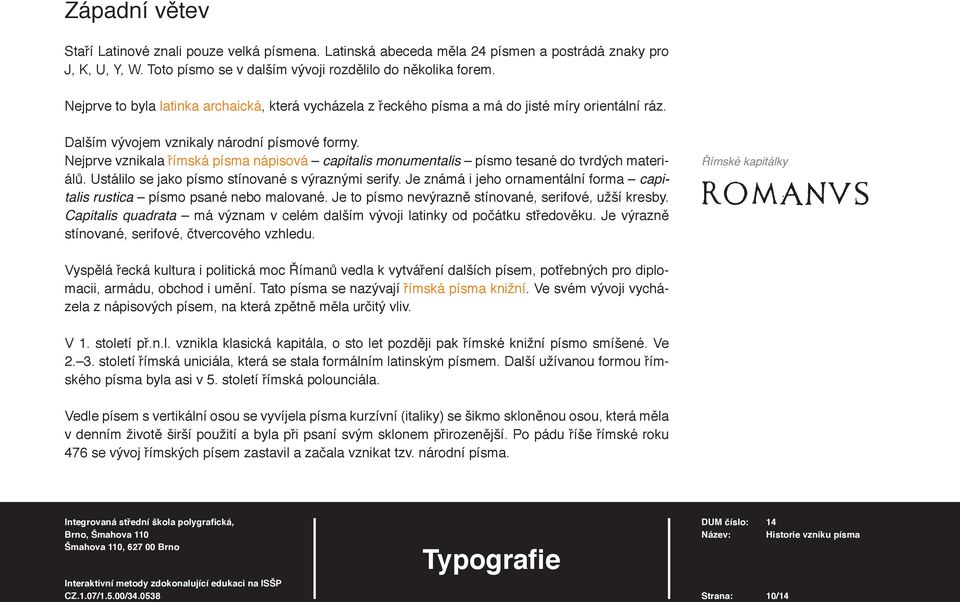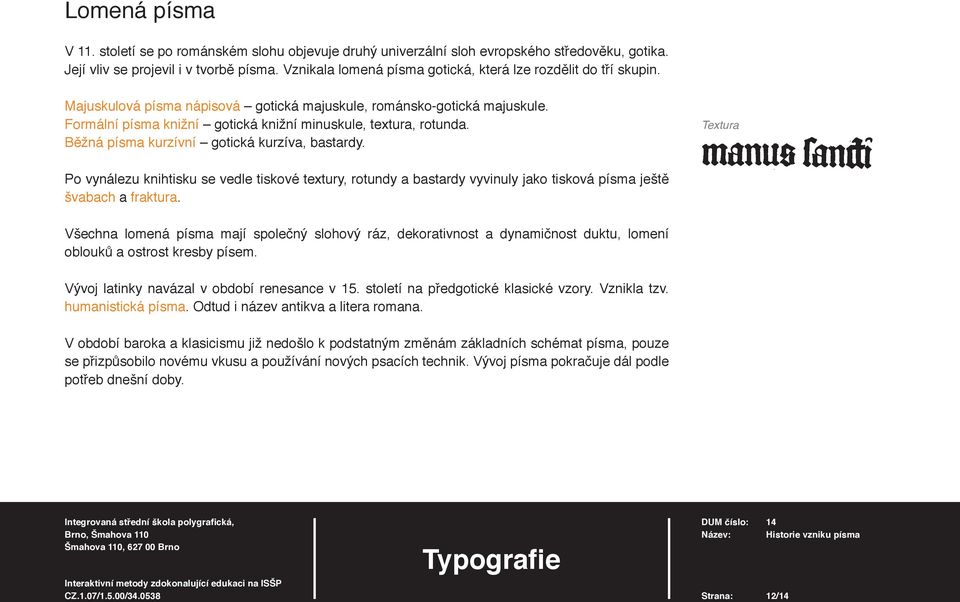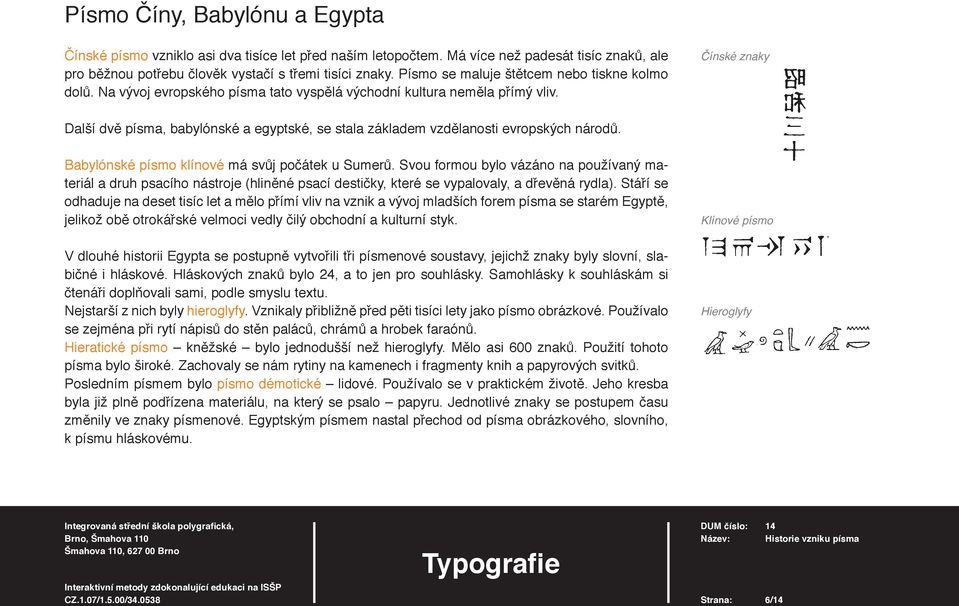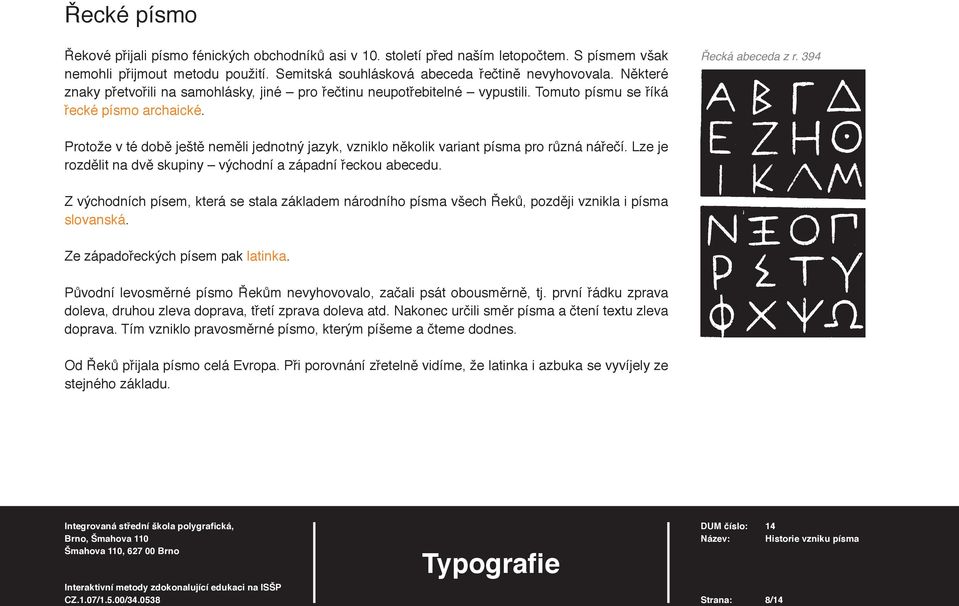
14. Historie vzniku písma. Typografie
1 14. Historie vzniku písma Vytvořila: Ivana Michálková Vytvořeno dne: Strana: 1/14
3 Řeč a písmo Podmínkou vzniku řeči a později písma byla praktická činnost lidí a společenský charakter práce, který vyžadoval vyjadřování a zaznamenávání myšlenek a skutečností. V dlouhých etapách vývoje lidstva nadešel čas, kdy ústní předávání zpráv a myšlenek nedostačovalo. Člověk vzal do ruky nástroj, aby zanechal zprávu pro další generace. Při sledování vývoje písma a tisku rozeznáváme dvě hlavní období, která jsou od sebe neoddělitelná a navzájem se doplňují. Každé z nich mělo podíl na současném stupni vývoje lidské společnosti. Předhistorické období vznik předchůdců písma piktogramy ideogramy Historické období vznik ručně psaných, kreslených nebo jinak utvářených písem vznik kovových tiskových písem a tisku vznik nových tiskových technik v 19. a 20. století moderní písmová tvorba Strana: 3/14
4 Předhistorické období Piktogramy zjednodušené kresby. Jejich smysl je jasný i bez znalosti jazyka. Později z nich vzniká obrázkové písmo. Některé národy zůstaly ve vývoji písma na této úrovni až do 19. století. Ideogramy symboly. V kulturně vyspělé oblasti Mezopotánie a Středomoří se v období otrokářského řádu začaly vyvíjet obrázkové ideogramy pro určitý pojem, který bylo možno vyjádřit mluvenou řečí. Předpokladem pro přečtení ideogramu byla znalost pojmu, který vyjadřoval. Lidstvo v hojné míře používá těchto symbolů dodnes. Co jsou symboly (loga) fi rem? Co jsou různá tetování na lidském těle? A když půjdeme dál, tak zjistíme, že snaha o vizuální komunikaci nás potkává na každém kroku. Např. navigace v metru, letištích, nemocnicích. Patří sem i dopravní značky, turistické značky, lodní abeceda, atd. Vývoj se však nezastavil. Z piktogramů a ideogramů se v příhodných podmínkách začalo tvořit písmo. Nejprve slovní, které se dále vyvíjelo, přes slabikové k hláskovému. Strana: 4/14
5 Historický vývoj písma Písmem rozumíme znaky, které mají sloužit k trvalému zaznamenávání myšlenek a skutečností. Je časově i místně nezávislé na osobě sdělujícího. Předpokladem pro přečtení písma a porozumění obsahu je nejen znalost písem (znaků), ale i znalost řeči (jazyka), v níž je písmo napsáno. Písmo Číny, Babylónu a Egypta Fénické písmo Řecké písmo východní (slovanské) hlaholice kyrilice ustav západní (latinka) archaická latinka římská písma nápisová, knižní Národní písma karolinská minuskule Lomená písma textura, rotunda, bastarda, švabach, fraktura Strana: 5/14
6 Písmo Číny, Babylónu a Egypta Čínské písmo vzniklo asi dva tisíce let před naším letopočtem. Má více než padesát tisíc znaků, ale pro běžnou potřebu člověk vystačí s třemi tisíci znaky. Písmo se maluje štětcem nebo tiskne kolmo dolů. Na vývoj evropského písma tato vyspělá východní kultura neměla přímý vliv. Čínské znaky Další dvě písma, babylónské a egyptské, se stala základem vzdělanosti evropských národů. Babylónské písmo klínové má svůj počátek u Sumerů. Svou formou bylo vázáno na používaný materiál a druh psacího nástroje (hliněné psací destičky, které se vypalovaly, a dřevěná rydla). Stáří se odhaduje na deset tisíc let a mělo přímí vliv na vznik a vývoj mladších forem písma se starém Egyptě, jelikož obě otrokářské velmoci vedly čilý obchodní a kulturní styk. V dlouhé historii Egypta se postupně vytvořili tři písmenové soustavy, jejichž znaky byly slovní, slabičné i hláskové. Hláskových znaků bylo 24, a to jen pro souhlásky. Samohlásky k souhláskám si čtenáři doplňovali sami, podle smyslu textu. Nejstarší z nich byly hieroglyfy. Vznikaly přibližně před pěti tisíci lety jako písmo obrázkové. Používalo se zejména při rytí nápisů do stěn paláců, chrámů a hrobek faraónů. Hieratické písmo kněžské bylo jednodušší než hieroglyfy. Mělo asi 600 znaků. Použití tohoto písma bylo široké. Zachovaly se nám rytiny na kamenech i fragmenty knih a papyrových svitků. Posledním písmem bylo písmo démotické lidové. Používalo se v praktickém životě. Jeho kresba byla již plně podřízena materiálu, na který se psalo papyru. Jednotlivé znaky se postupem času změnily ve znaky písmenové. Egyptským písmem nastal přechod od písma obrázkového, slovního, k písmu hláskovému. Klínové písmo Hieroglyfy Strana: 6/14
7 Fénické písmo V druhém tisíciletí před naším letopočtem žili na území dnešní Sýrie Féničané, kteří vytvořili souhláskovou, tzv. severosemitskou abecedu o 22 písmenech. Přímí vliv egyptského písma na fénické není prokazatelný ani v grafi cké formě. Z fénického písma vzniklo 80 procent známých abecedních soustav. Západosemitští Féničané byli zdatnými obchodníky a mořeplavci. Pronikli do všech moří mezi Afrikou, Asií a Evropou. Je možné, že severogermánské runy (runa = tajemství) o 24 písmenech, staré asi dva tisíce let, jsou odvozeny od fénického písma. I na ostrově Kypru v Egejském moři byly ve vykopávkách nalezeny fénické nápisy. Fénické písmo se psalo zprava doleva. Strana: 7/14
8 Řecké písmo Řekové přijali písmo fénických obchodníků asi v 10. století před naším letopočtem. S písmem však nemohli přijmout metodu použití. Semitská souhlásková abeceda řečtině nevyhovovala. Některé znaky přetvořili na samohlásky, jiné pro řečtinu neupotřebitelné vypustili. Tomuto písmu se říká řecké písmo archaické. Řecká abeceda z r. 394 Protože v té době ještě neměli jednotný jazyk, vzniklo několik variant písma pro různá nářečí. Lze je rozdělit na dvě skupiny východní a západní řeckou abecedu. Z východních písem, která se stala základem národního písma všech Řeků, později vznikla i písma slovanská. Ze západořeckých písem pak latinka. Původní levosměrné písmo Řekům nevyhovovalo, začali psát obousměrně, tj. první řádku zprava doleva, druhou zleva doprava, třetí zprava doleva atd. Nakonec určili směr písma a čtení textu zleva doprava. Tím vzniklo pravosměrné písmo, kterým píšeme a čteme dodnes. Od Řeků přijala písmo celá Evropa. Při porovnání zřetelně vidíme, že latinka i azbuka se vyvíjely ze stejného základu. Strana: 8/14
9 Východní větev Tvůrcem nejstaršího slovanského písma hlaholice (glagolica) byl soluňský učenec Konstantin Filosof (později přijal jméno Kyrillos Cyril), který přišel se svým bratrem Metodějem kolem roku 855 do Velkomoravské říše, aby šířil křesťanství mezi západními Slovany. O jejich příchod požádal kníže Rostislav byzantského císaře Michala III. z politických důvodů, neboť našim národům hrozila od franckých kněží germanizace. Hlaholice a kyrilice Konstantin použil běžné malé řecké písmo a doplnil je několika znaky hebrejsko-samuritskými Hlaholice měla dvě formy: okrouhlou a hranatou. Bylo to písmo velmi složité, mělo 43 znaků a jeho čitelnost byla obtížná. Hlaholice se v Čechách udržela asi do 11. století. Nejprve paralelně s latinkou, později se od jejího užívání upustilo. Ve starém Velkém Bulharsku, kam po odchodu z Čech Metoděj přišel, se vedle hlaholice rozšířila praktičtější kyrilice. Svůj název dostalo toto písmo na počest Cyrila, který byl prohlášen za svatého. Odtud se kyrilice šířila do Srbska, na Ukrajinu a do Ruska. Ruská azbuka vychází z kyrilice, která se na Ukrajině a v Rusku již vyvíjela samostatně. Sloužila hlavně k psaní náboženských knih a textů. Říkalo se jí ustav. V roce 1708 nechal car Petr Veliký písmo zjednodušit podle latinkových vzorů v novou občanskou abecedu a nazval ji graždanka. Ta se používá v podstatě dodnes. Strana: 9/14
10 Západní větev Staří Latinové znali pouze velká písmena. Latinská abeceda měla 24 písmen a postrádá znaky pro J, K, U, Y, W. Toto písmo se v dalším vývoji rozdělilo do několika forem. Nejprve to byla latinka archaická, která vycházela z řeckého písma a má do jisté míry orientální ráz. Dalším vývojem vznikaly národní písmové formy. Nejprve vznikala římská písma nápisová capitalis monumentalis písmo tesané do tvrdých materiálů. Ustálilo se jako písmo stínované s výraznými serify. Je známá i jeho ornamentální forma capitalis rustica písmo psané nebo malované. Je to písmo nevýrazně stínované, serifové, užší kresby. Capitalis quadrata má význam v celém dalším vývoji latinky od počátku středověku. Je výrazně stínované, serifové, čtvercového vzhledu. Římské kapitálky Vyspělá řecká kultura i politická moc Římanů vedla k vytváření dalších písem, potřebných pro diplomacii, armádu, obchod i umění. Tato písma se nazývají římská písma knižní. Ve svém vývoji vycházela z nápisových písem, na která zpětně měla určitý vliv. V 1. století př.n.l. vznikla klasická kapitála, o sto let později pak římské knižní písmo smíšené. Ve století římská uniciála, která se stala formálním latinským písmem. Další užívanou formou římského písma byla asi v 5. století římská polounciála. Vedle písem s vertikální osou se vyvíjela písma kurzívní (italiky) se šikmo skloněnou osou, která měla v denním životě širší použití a byla při psaní svým sklonem přirozenější. Po pádu říše římské roku 476 se vývoj římských písem zastavil a začala vznikat tzv. národní písma. Strana: 10/14
11 Národní písma Vývoj národních písem je velmi složitý. Většinou vycházejí z římských vzorů, jejich grafi cké formy a upotřebení jsou však značně rozdílné. Dávají svědectví o vývoji jednotlivých národů a odrážejí mocenské a kulturní proudy Evropy od 5. do 11. století. Podnět k větší jasnosti a čitelnosti písmové kresby a k prvnímu stabilizování forem naší malé abecedy dal Karel Veliký, který vládl francké říši v letech Vyhlásil reformu písma a jeho zásluhou vznikla dobře čitelná rukopisná forma malých písmen. Podle svého původu se nazývá karolínská minuskule. Karolínská minuskule Strana: 11/14